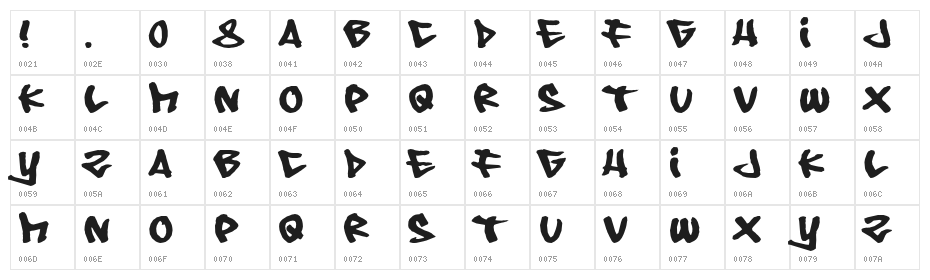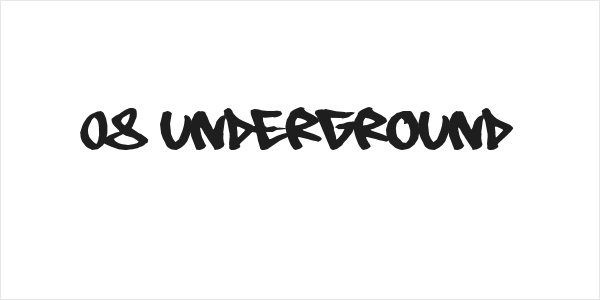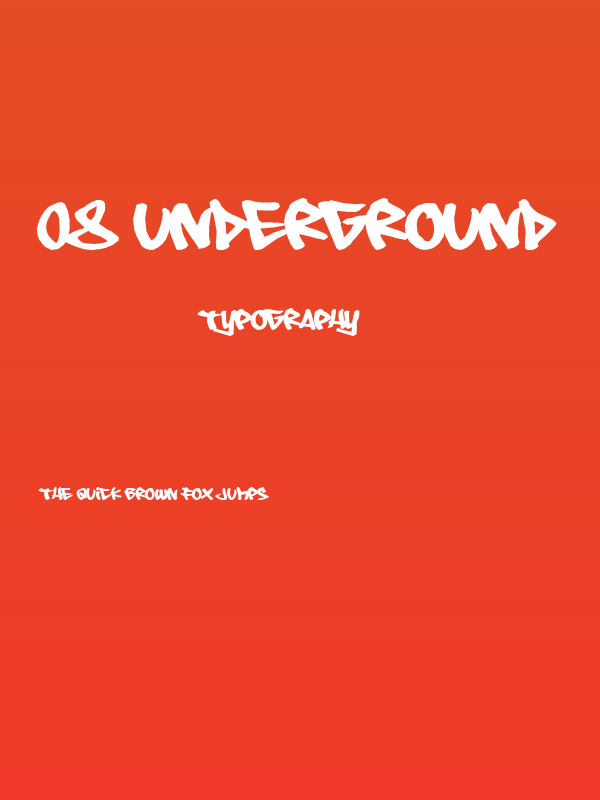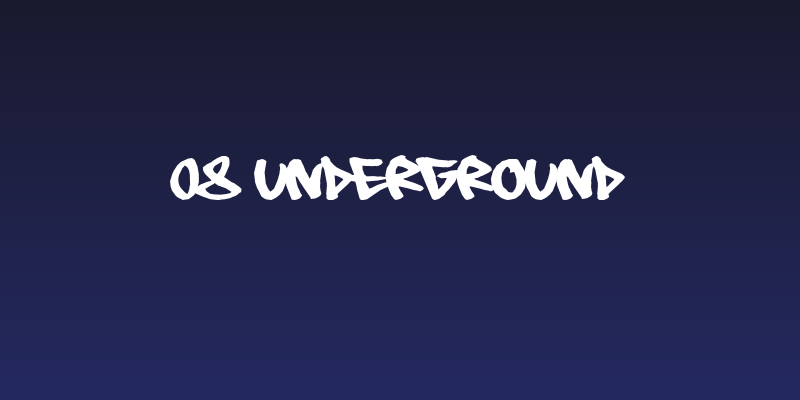
08 Underground Font
✎ Graffiti
| 分类 | Graffiti |
| 整体风格 | Urban, Edgy, Youthful |
| 使用场景 | Logos, Headlines, Posters |
| 推荐项目 | Perfect for street art designs, urban-themed posters, music album covers, and youth-oriented branding. |